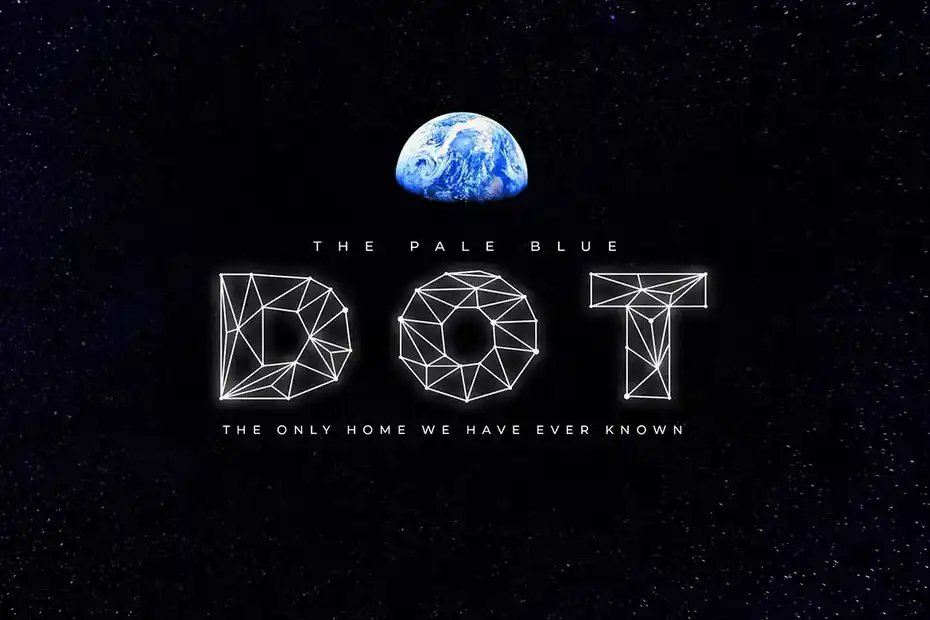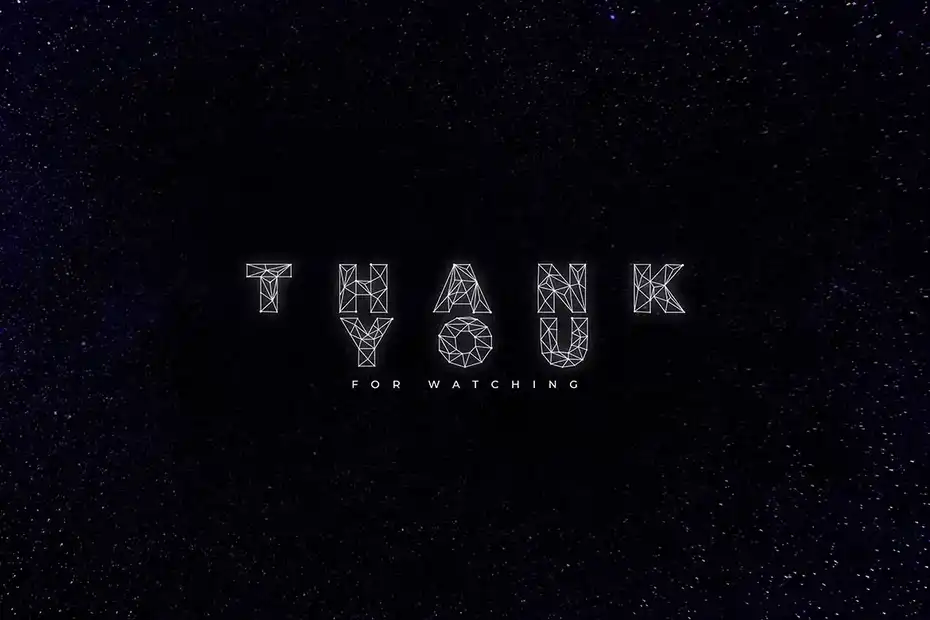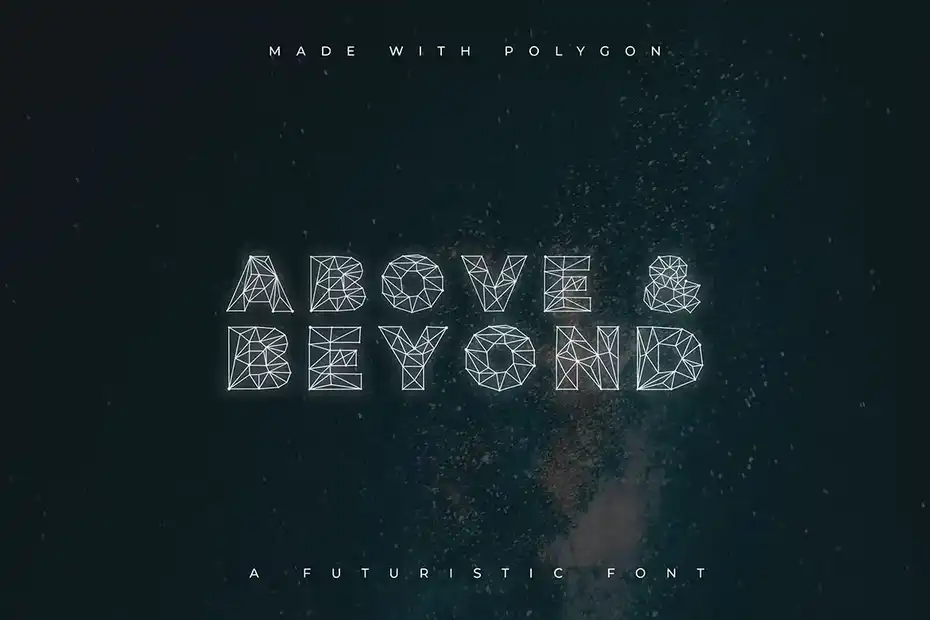
دانلود فونت تکنولوژی چند ضلعی : این مجموعه شامل یک فونت گرافیکی تکنولوژی چند ضلعی است که برای پروژه های فناوری پیشرفته، واقعیت مجازی و هوش مصنوعی مناسب میباشد. فونت های گرافیکی می توانند جذابیت طرح های شما را چندین برابر کنند، در دسته بندی فونت انگلیسی گرافیکی در سیجی کوک می توانید فونت های گرافیکی بیشتری را دانلود کنید.
- عنوان مجموعه: Polygon Technology Font
- سبک: Serif